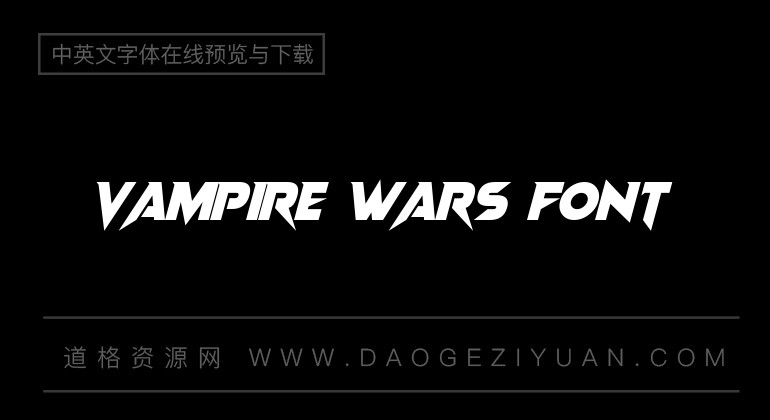
Vampire Wars Font
Vampire Wars Font 是一种由 Blambot 制作的字体,Blambot 是一家致力于为漫画、动画、电影等娱乐产业提供高质量字体的公司。Vampire Wars Font 是一种设计精美的字体,其风格灵感来源于传说中的吸血鬼和恐怖片。这种字体的特点是有很多锐利的棱角和曲线,让文字看起来很有力量感和神秘感。它常常被用于制作海报、广告、漫画书、书籍封面等需要突出恐怖或幻想元素的场合。
Vampire Wars Font是一款非常不错的手写艺术字体,具有很好的视觉感,适合于文化类的宣传设计、商业类品牌的广告和产品包装设计以及个性化文字排版等较多场景。